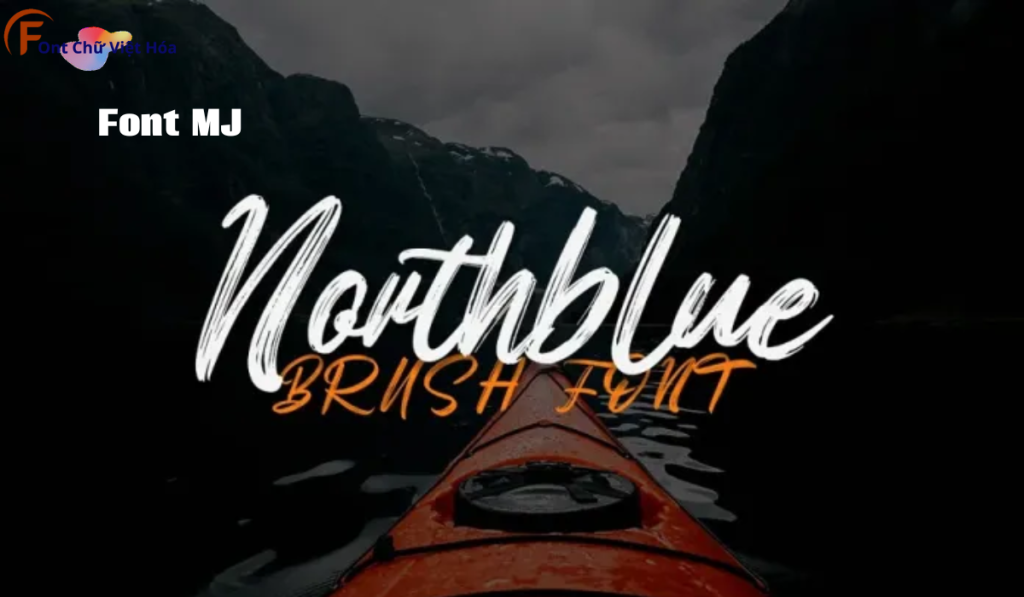
Font MJ NorthBlue Việt Hóa
Tác giả: MJ North Blue
Bộ Font: MJ
Font MJ NorthBlue Việt Hóa là một font chữ không chân cá tính, thuộc bộ font MJ. Được thiết kế với mục tiêu mang lại sự độc đáo và sáng tạo, font này lý tưởng cho các dự án thiết kế như logo, poster, và bao bì sản phẩm. Với các nét chữ sắc nét và độ dày đều đặn, Font MJ NorthBlue Việt Hóa không chỉ dễ đọc mà còn tạo cảm giác hiện đại và phá cách. Việc Việt hóa font giúp người dùng dễ dàng sử dụng trong các thiết kế tiếng Việt, mang lại sự tiện lợi và thẩm mỹ cao.